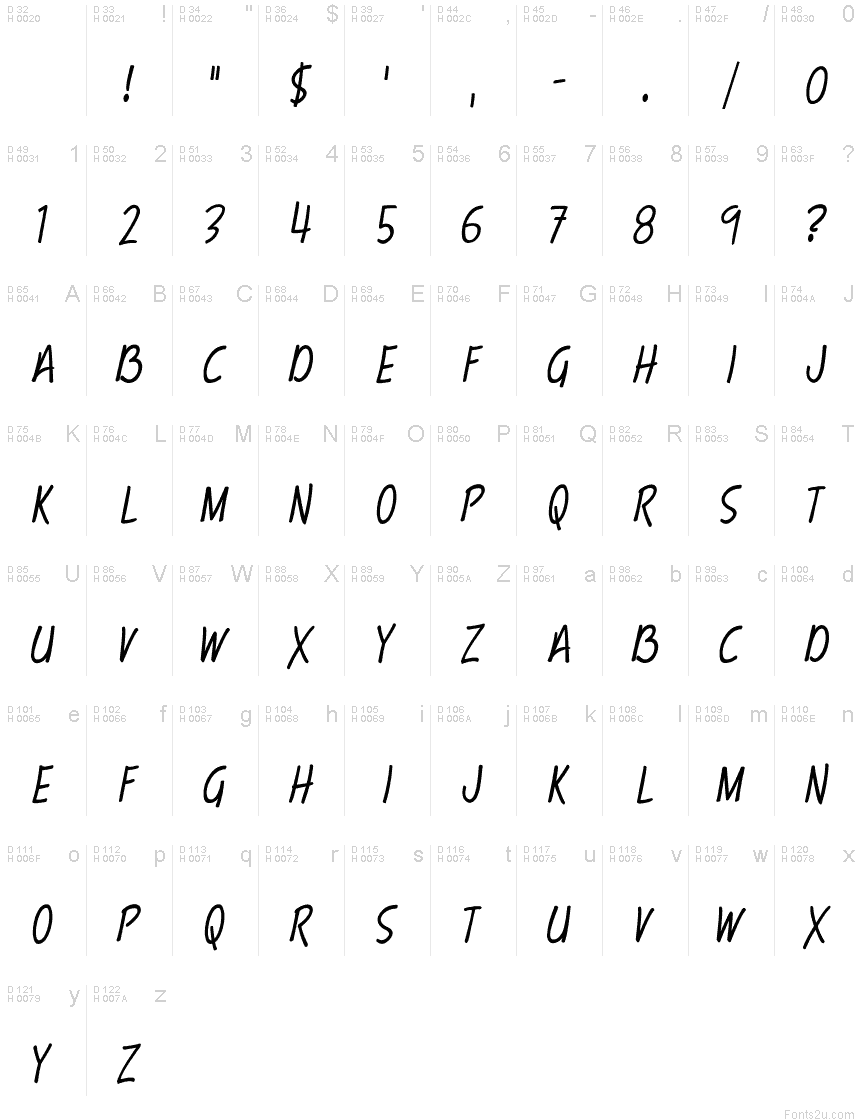
Terry Script autorstwa Vic Fiegera to bezpłatny, komiksowy krój pisma imitujący odręczne pismo wykonane markerem. Litery mają surową, niezobowiązującą energię – szerokie pociągnięcia, zaokrąglone końcówki i lekkie drżenie sprawiają, że całość wygląda jak szybko nabazgrana na plakacie lub okładce zeszytu, a nie starannie wyrysowana.
Dzięki temu jest to naturalny wybór do zinów, okładek książek dla dzieci, plakatów szkolnych, tytułów komiksów i zabawnych opakowań, gdzie zbyt schludne wykończenie wydawałoby się zbyt sztywne. Świetnie sprawdza się również w krótkich nagłówkach i na etykietach, ponieważ luźny, dynamiczny rytm sprawia, że nawet pojedyncze słowo wydaje się żywe i ludzkie.